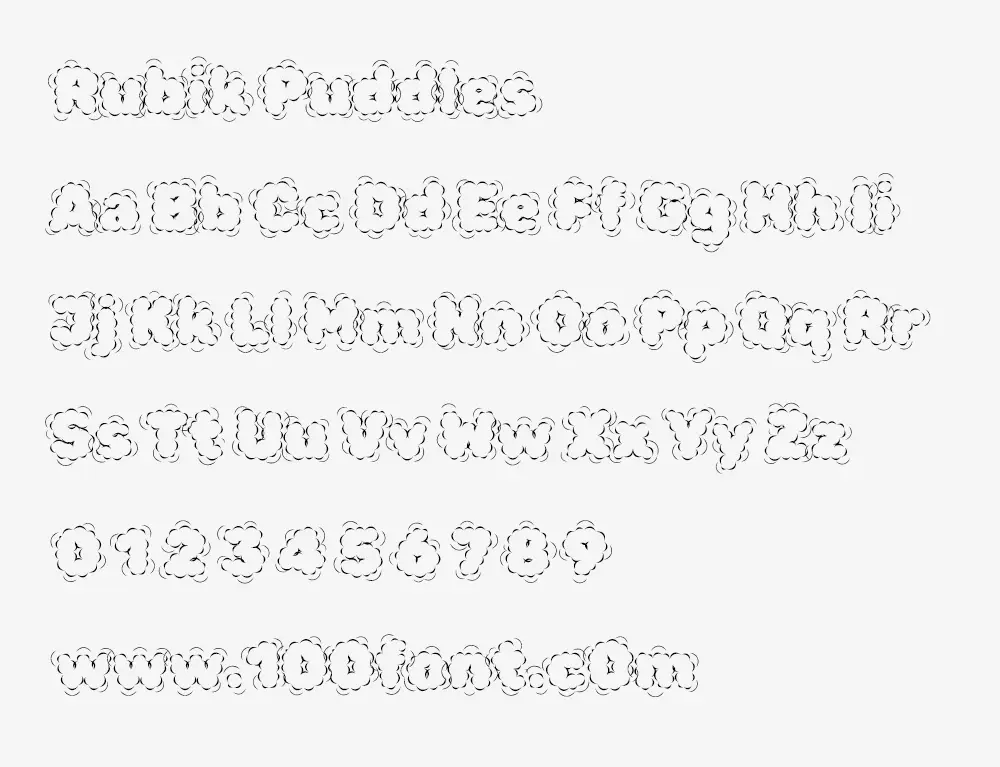
Rubik Filtered Fonts是基於Hubert & Fischer,Meir Sadan和Cyreal的GoogleFont Rubik的原始腳本生成設計。用於生成它的代碼可以在 https://github.com/NaN-xyz/Glyph-Filters 中找到。
Rubik Filtered Fonts are original, script-generated design based on the GoogleFont Rubik by Hubert & Fischer, Meir Sadan and Cyreal. The code used to generate it can be found at https://github.com/NaN-xyz/Glyph-Filters.